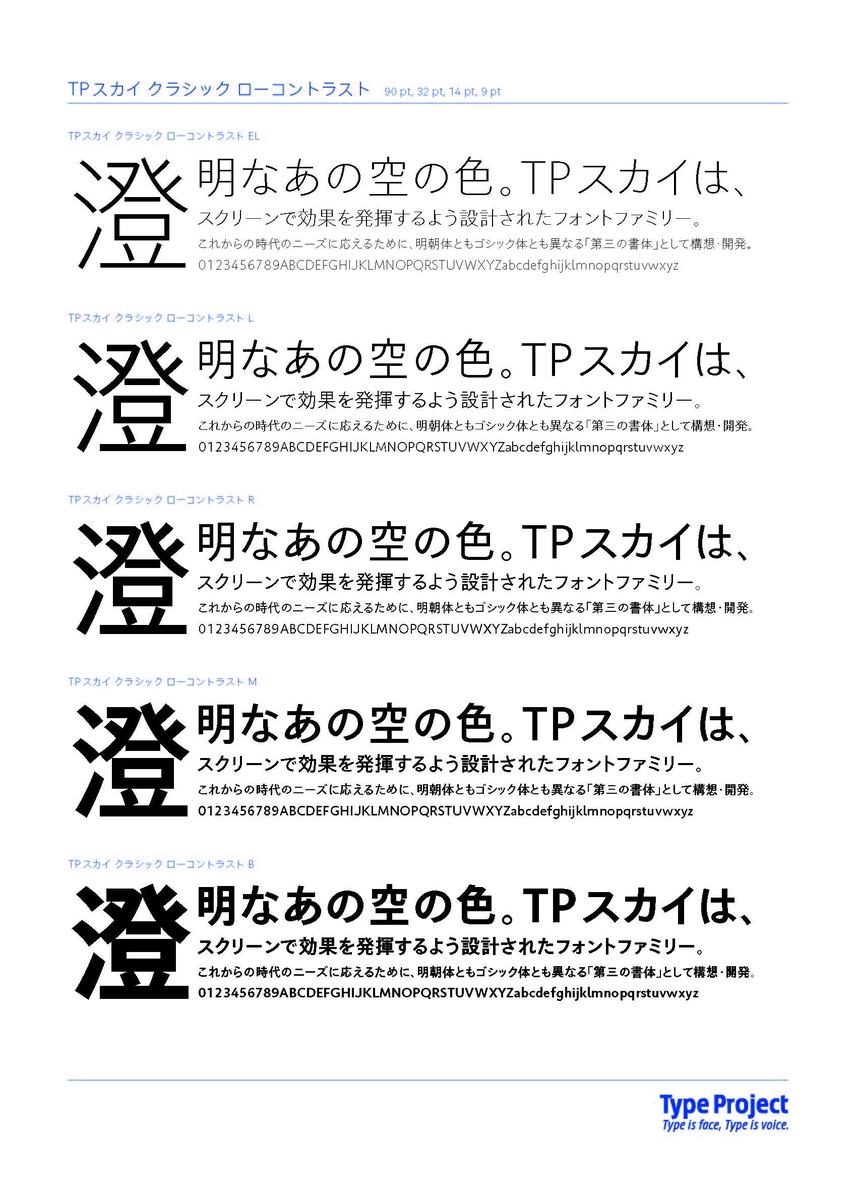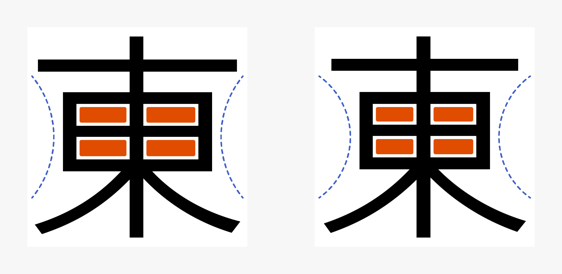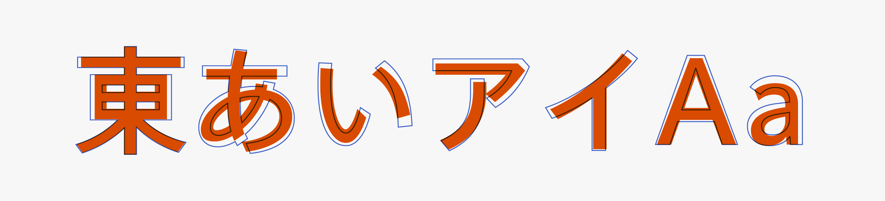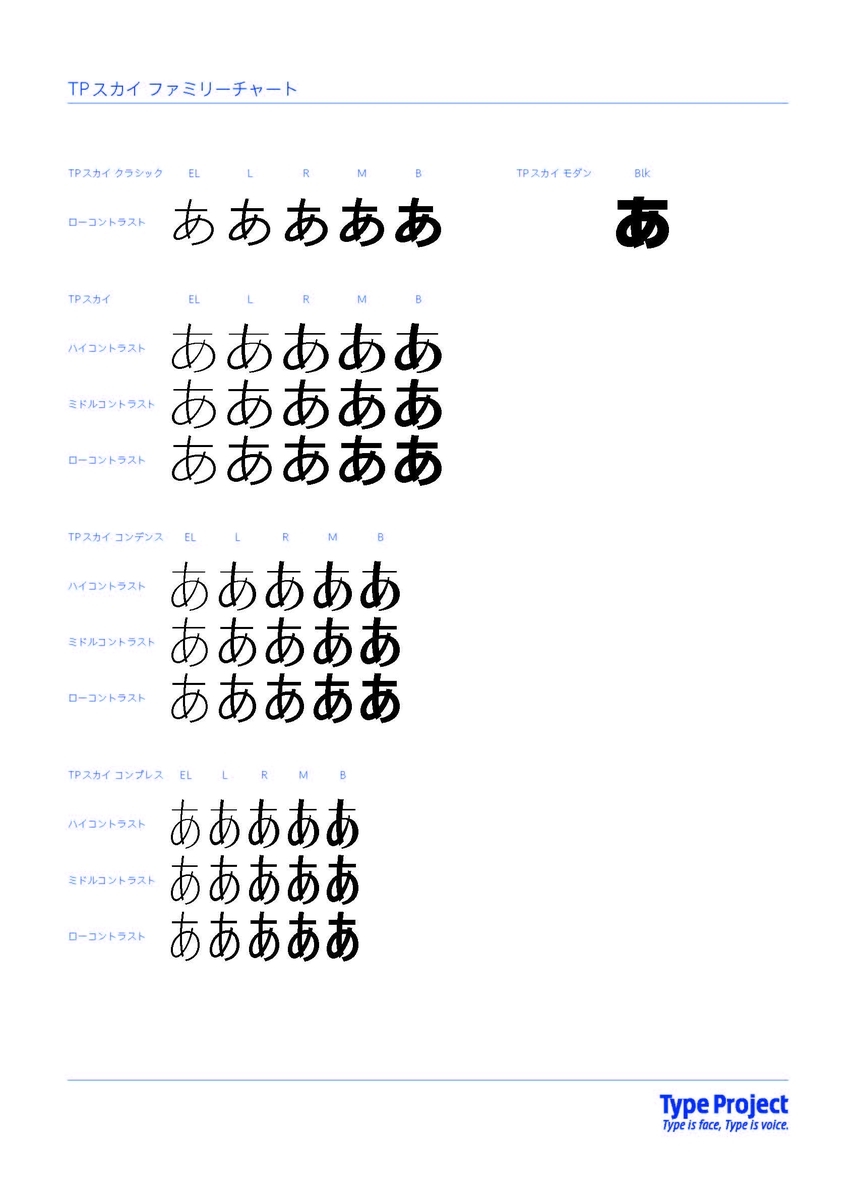
TPスカイ クラシック ローコントラスト
タイププロジェクトは、スクリーン表示に最適なフォント「TPスカイ」ファミリーに、フォーマルな場面における用途の拡大を目指し、均整の取れた楷書のプロポーションを取り入れた「TPスカイ クラシック ローコントラスト」を追加したことを発表した。
TPスカイ クラシックは、初唐の楷書*を頂点とするフトコロ(字画内の内部空間)の引き締まった漢字をクラシックの典拠として位置づけている。
ファミリー全体を包含するコンセプト「澄み渡った広大な空」をベースに、サンセリフ体の簡潔明快さと古典的な楷書の端正さを合わせもつ書体となる。
漢字・仮名・欧文を貫く均整の取れたプロポーションは、画面を引き締めると同時に落ち着いた雰囲気を醸し出す。
(*初唐の楷書:中国、唐時代の文学史を4期に区分した、その第1期。唐初の618年から、玄宗の即位前年までの100年)
また、TPスカイファミリー共通の表示適性、すなわち、簡潔で滑らかなアウトライン描画を徹底することによって、フォントファイルのサイズを極限まで抑えている。
TPスカイ クラシックは、古典書体に範を取り、TPスカイが持つ中庸な骨格のフトコロを引き締めたデザインになっている。
「TPスカイ クラシックは、古典的でフトコロを引き締めた骨格と、シンプルなアウトライン描画を両立したフォントで、フォーマルな場面によく似合います。従来のTPスカイファミリーに、TPスカイ クラシックが加わることで、場面に応じた使い分けができるので、新しい表現の幅が広がると思います」
TPスカイは、45フォント(5ウエイト×3コントラスト×3つの字幅)のラインナップに、TPスカイ モダンBlkとTPスカイ クラシック ローコントラスト(5ウエイト)が加わり、51フォントのファミリーになった。
TPスカイの各フォントを使い分けることで、本文と見出し、タイトルとキャプションの関係を効果的に表現し、画面に高いレベルの統一感をもたらす。
TPスカイクラシック
ウエイト:EL(エクストラライト)、L(ライト)、R(レギュラー)、M(ミディアム)、B(ボールド)